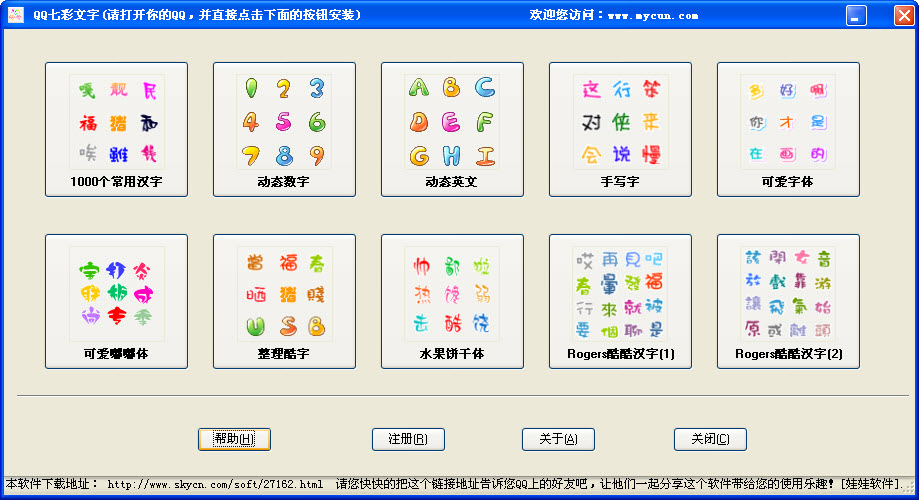
qq七彩字体
七彩字体是专为喜欢用qq聊天的朋友提供的一款字体更换软件,这款字体非常的具有特色,能够让你的聊天信息变得更加炫彩夺目,而且都是可以免费永久使用的,不会收取任何费用,有需要的朋友就请来绿色资源网下载使用吧!
qq七彩字体介绍
QQ七彩字体是款在线下载各种特色的七彩字体下载工具。
七彩生活 七彩阳光
每一种颜色代表一种心情
我的QQ也要七彩
用《QQ七彩文字》亮出你的QQ文字